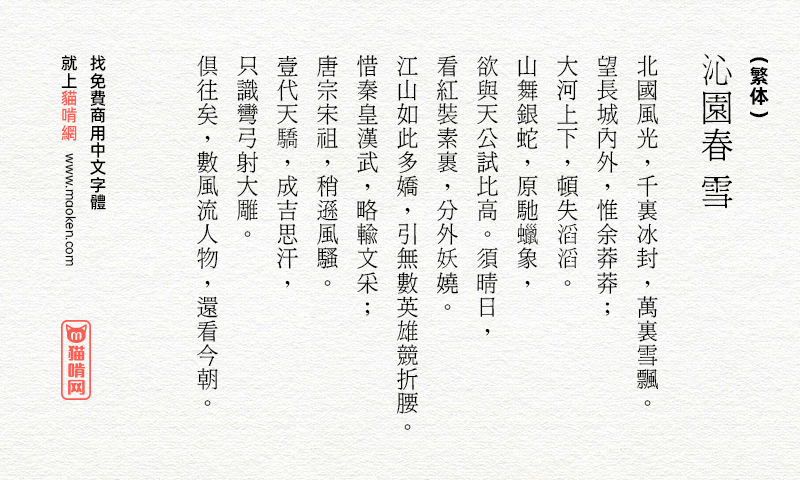
《台湾明体》cwTeX字体来源可能是盗版字体 不建议商业使用
台湾明体cwTeXMing是一款旧字形外观,在一定程度上仿照古籍《康熙字典》字体,字形构架 稳固,庄重而大方,适用於古籍文献印刷。
cwTeX 字型最初是由 Tsong-Min Wu 及 Tsong-Huey Wu 于 1999 至 2004 年间製作并以 GNU GENERAL PUBLIC LICENSE Version 2 or latter 发佈。在 2005 至 2007 年间,Edward G.J. Lee 对该字型进行过整理。本专案 cwtex-q-fonts 自 2008 年起由 Chen-Pan Liao 开始运作。
于 2014 年,Tsong-Min Wu、Tsong-Huey Wu、Edward G.J. Lee 及 Chen-Pan Liao 四人同意将汉字及中文常用标点符号之字符另外独立并以 SIL Open Font License (Version 1.1) 授出,以利与其他 OFL 授权之字体整合。